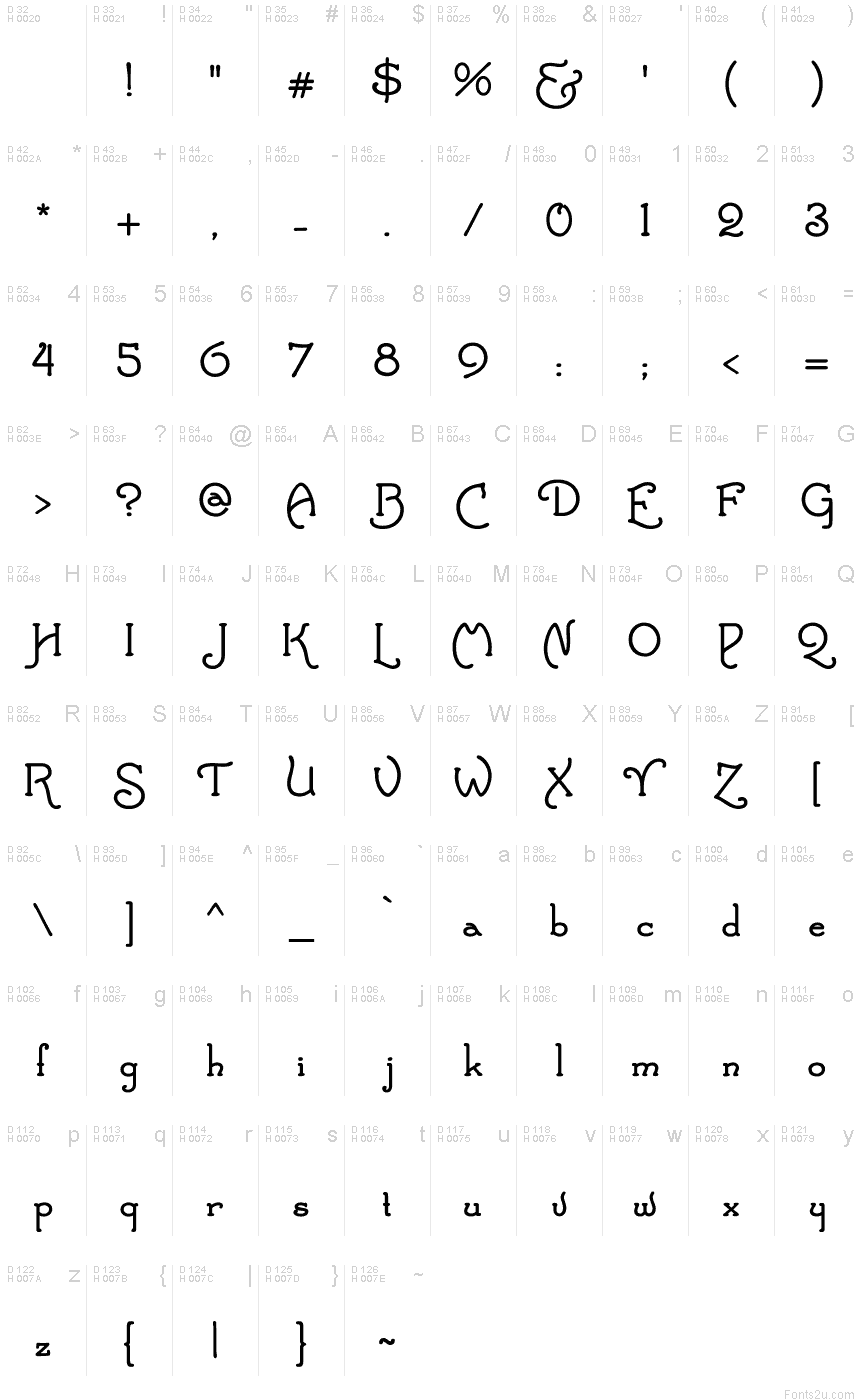
<p>Santa's Sleigh Full Bold von HT. ist eine kostenlose Display-Schrift für weihnachtliche Geschichten mit einem Hauch von viktorianischem Charme. Die runden, bauchigen Kleinbuchstaben, gepaart mit einem schwungvollen großen S und feinen, tropfenförmigen Endungen, verleihen dem gesamten Zeichensatz eine gemütliche, nostalgische Weihnachtsstimmung – ohne dabei zu verspielt oder kitschig zu wirken.</p>
<p>Dadurch eignet sie sich perfekt für saisonale Plakate, Geschenkanhänger, Einladungen, Verpackungen und Ladenschilder, bei denen eine kostenlose Schrift zwar festlich wirken, aber nicht in den Comic-Stil abdriften soll. Sie funktioniert auch hervorragend für kurze Buchtitel, Menü-Überschriften und Karten, da die geschwungenen Details und vollen Kurven selbst bei wenigen Wörtern für ausreichend Charakter sorgen.</p>